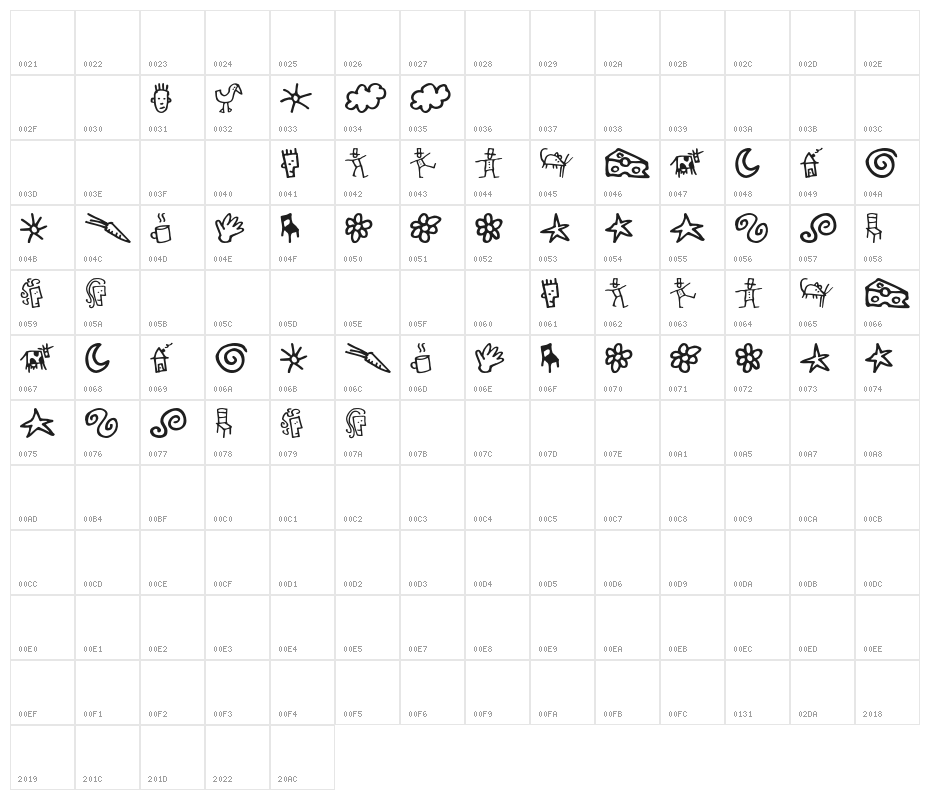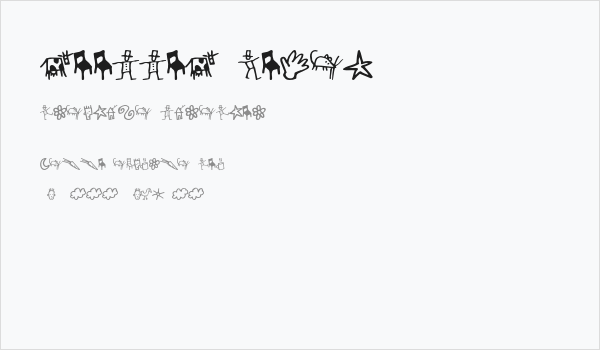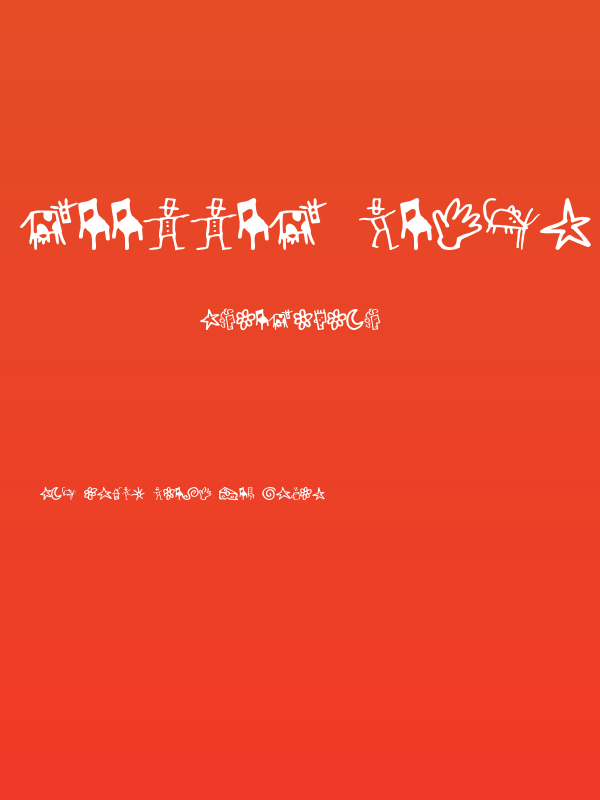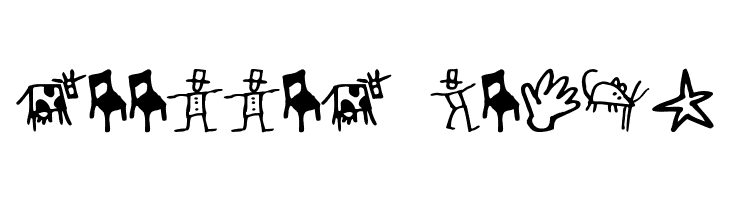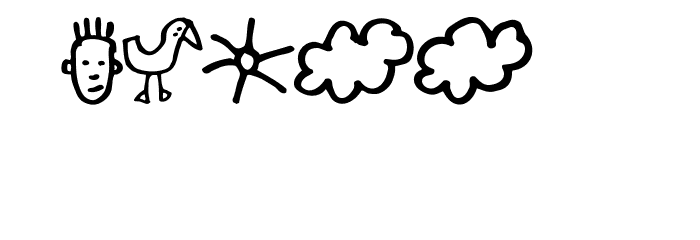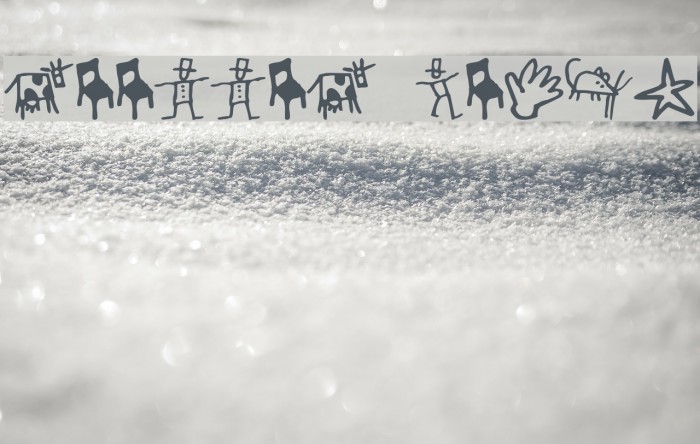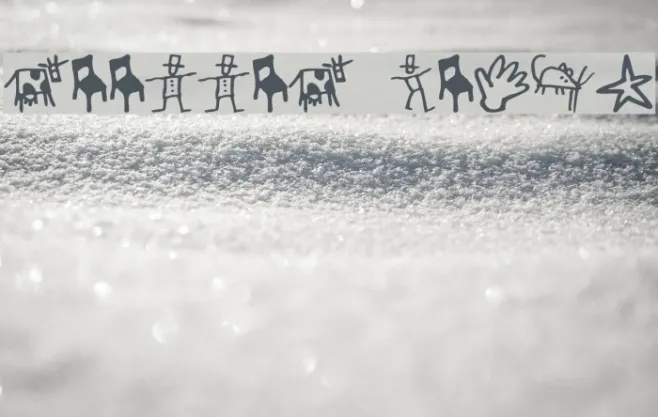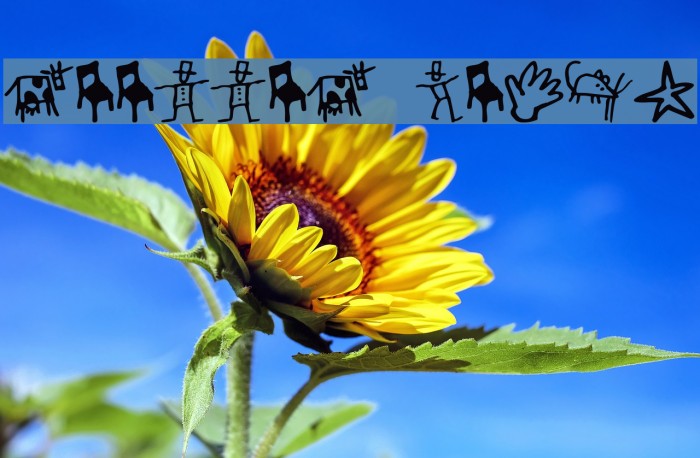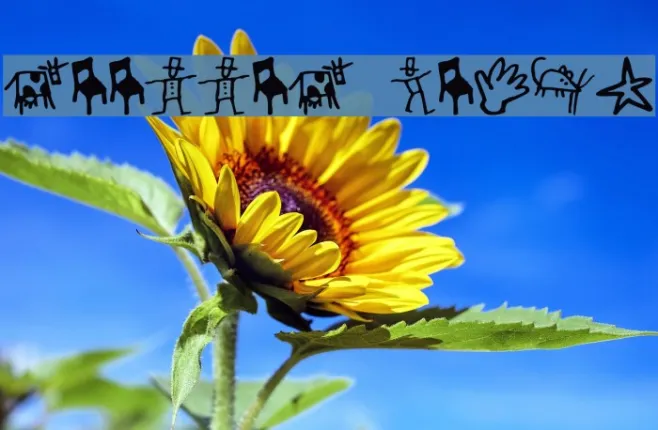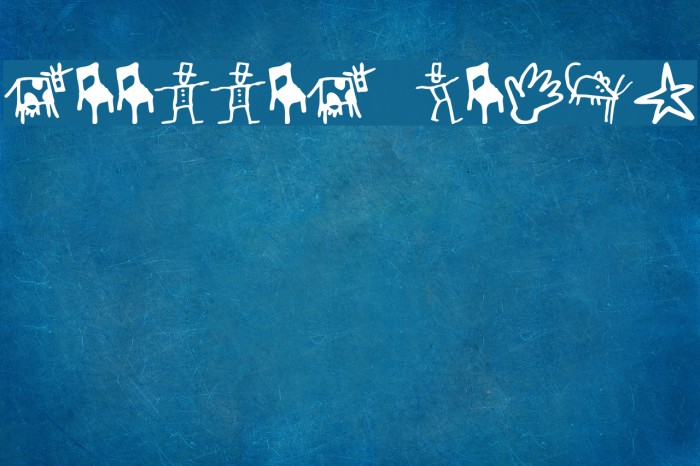
GoodDog-Bones Font
| Stile generale | Playful, Artistic, Whimsical |
| Caso d'uso | Decorative elements, Illustrations, Creative designs |
| Progetti proposti | Ideal for children's books, playful invitations, creative posters, and fun branding projects. |